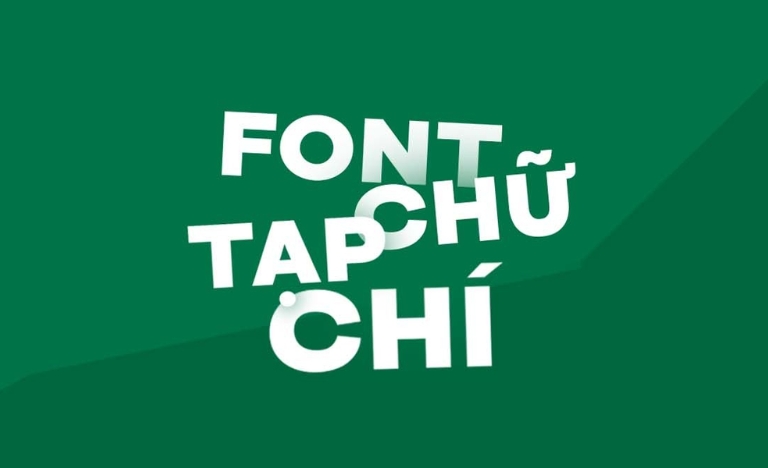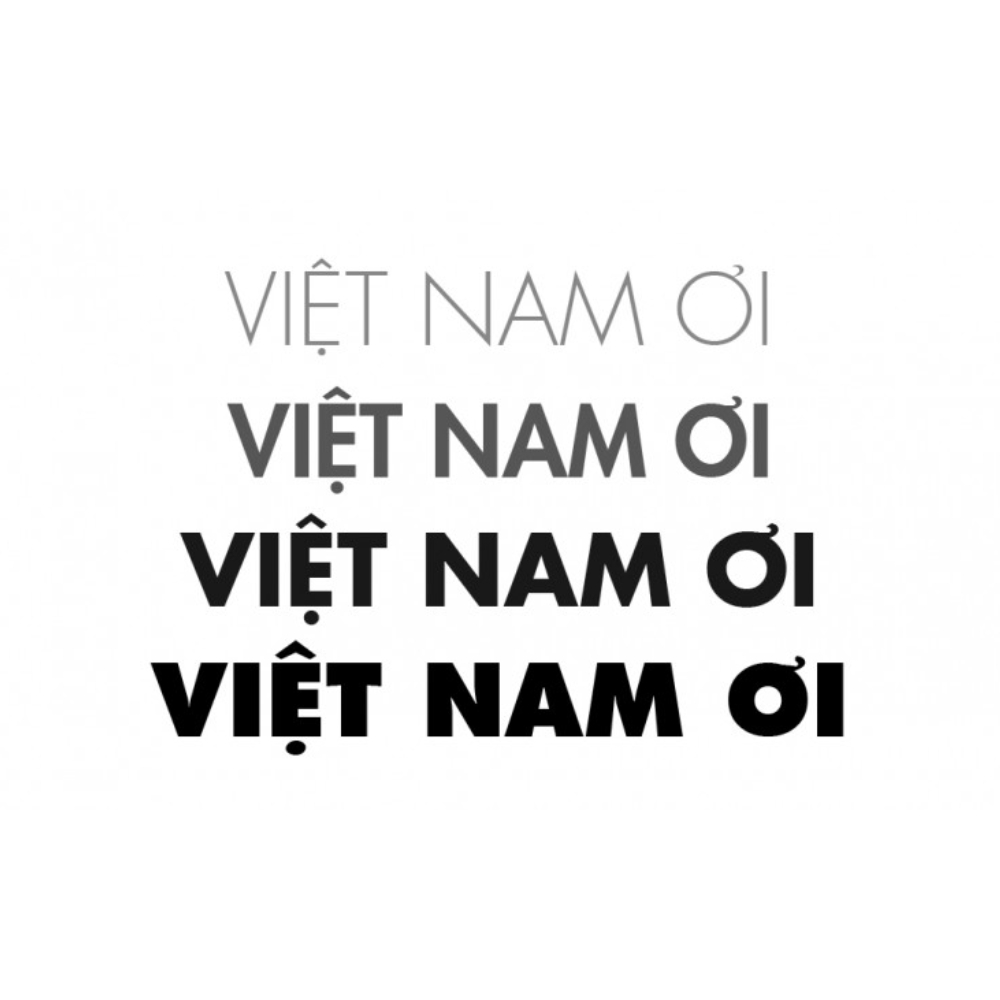
Trong lĩnh vực thiết kế đồ họa và trình bày hồ sơ kiến trúc, việc sử dụng các bộ font chữ tạp chí Việt hóa giúp nâng tầm thẩm mỹ, mang lại vẻ ngoài sang trọng và chuyên nghiệp cho văn bản. Đặc trưng của dòng font này là sự chỉn chu trong cấu trúc và khả năng thu hút thị giác mạnh mẽ, phù hợp cho các bìa hồ sơ dự án, brochure giới thiệu homestay hay các ấn phẩm truyền thông cao cấp.
Đặc điểm thẩm mỹ của các dòng font chữ tạp chí Việt hóa
Dòng font này thường được chia thành hai nhóm chính: nhóm có chân với độ tương phản cao mang nét cổ điển, thanh lịch và nhóm không chân tối giản mang hơi thở hiện đại. Điểm nổi bật của font chữ tạp chí Việt hóa chính là việc tối ưu hóa bộ dấu tiếng Việt sao cho cân đối với các đường nét thanh đậm đặc trưng, giúp văn bản duy trì được sự đẳng cấp của bộ chữ gốc mà không gặp tình trạng lỗi hiển thị ký tự.
Sự ổn định của các bộ font này còn thể hiện ở khả năng định hình phong cách cho toàn bộ bản thiết kế. Những đường nét sắc sảo, dứt khoát giúp các tiêu đề trở nên nổi bật, tạo ra nhịp điệu thị giác lôi cuốn cho người đọc. Đây là lựa chọn phù hợp cho những ai muốn tìm kiếm sự giao thoa giữa tính nghệ thuật của font chữ báo chí truyền thống và sự linh hoạt của xu hướng thiết kế đương đại.
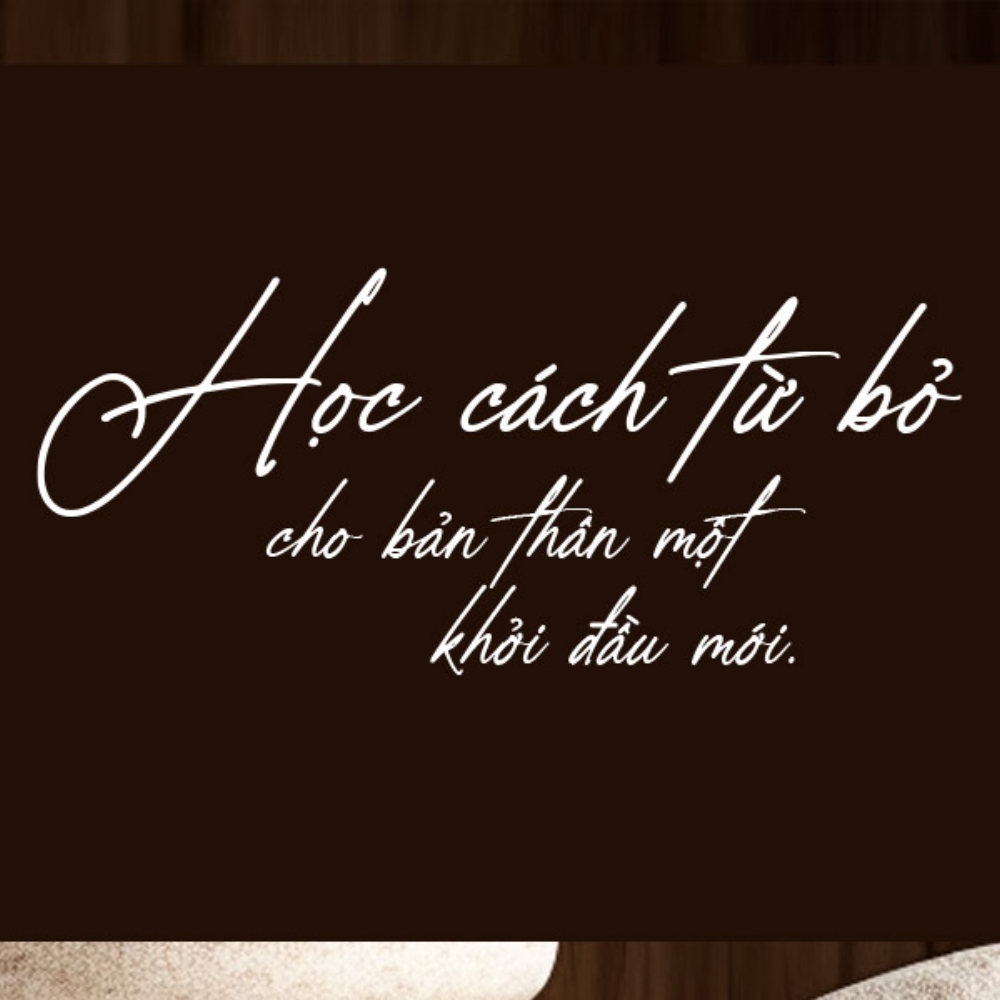
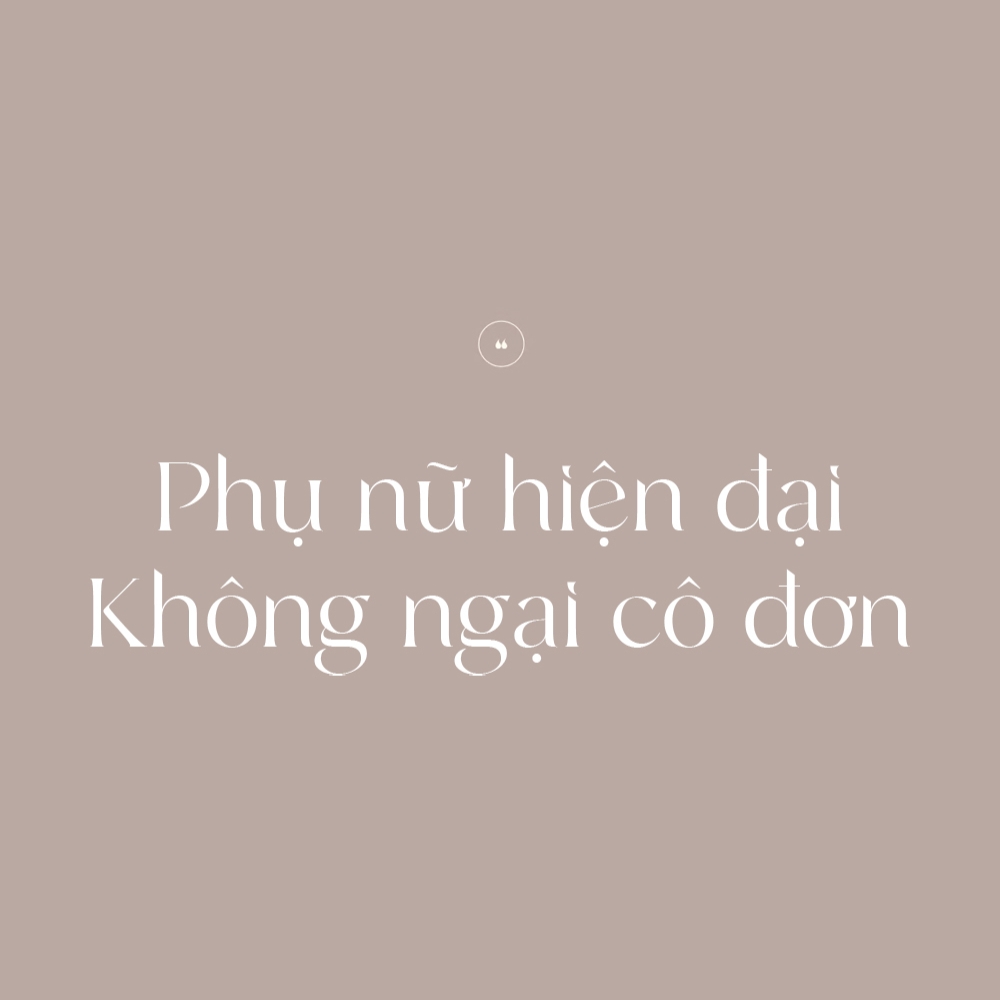
Phân loại và tải các nhóm font chữ báo chí và thời trang phổ biến
Tùy vào mục tiêu truyền tải và đối tượng người xem, bạn có thể lựa chọn các nhóm font chữ phù hợp để đạt được hiệu quả thị giác như mong muốn.
| Nhóm Font | Đặc điểm thiết kế | Mục đích sử dụng |
|---|---|---|
| Didone / Modern Serif | Tương phản nét thanh đậm cực cao, sang trọng | Font chữ tạp chí Vogue, thời trang cao cấp |
| Transitional Serif | Cân đối, dễ đọc, mang tính chính thống | Nội dung báo chí, thuyết minh dự án kiến trúc |
| Geometric Sans-serif | Hình học tối giản, hiện đại, thông thoáng | Tạp chí kiến trúc, nội thất, phong cách Industrial |
| Humanist Sans | Nét chữ mềm mại, mang hơi hướng viết tay | Tạp chí phong cách sống, đời sống xã hội |
Gợi ý phối hợp: Đối với các hồ sơ năng lực dự án nhà lắp ghép hoặc homestay, bạn nên sử dụng một font chữ tạp chí thời trang cho các tiêu đề chính và kết hợp cùng một font chữ không chân tối giản cho phần nội dung chi tiết. Sự phân cấp này giúp bản thiết kế của bạn trông chuyên nghiệp và mạch lạc hơn.
03 Ứng dụng font chữ tạp chí thời trang vào thiết kế kiến trúc
Nhờ vẻ ngoài giàu tính thẩm mỹ và chuyên nghiệp, bộ font này mang lại giá trị thực tế cao khi được ứng dụng vào các hạng mục quảng bá và trang trí không gian:
- Thiết kế hồ sơ năng lực dự án: Sử dụng Font chữ tạp chí Vogue cho các tiêu đề trang mục giúp thể hiện tư duy thẩm mỹ sắc sảo, tạo ấn tượng mạnh mẽ về năng lực của đơn vị thiết kế đối với chủ đầu tư.
- Nhận diện cho Homestay & Boutique Hotel: Những nét chữ thanh lịch của dòng font thời trang rất ăn ý khi xuất hiện trên các bảng hiệu mica, inox gương hoặc các ấn phẩm hướng dẫn khách hàng tại khu nghỉ dưỡng.
- Bảng biển trang trí nội thất: Bạn có thể dùng font này để làm decal dán tường hoặc in tranh trang trí tại sảnh chờ văn phòng container, mang lại cảm giác thời thượng và đẳng cấp cho không gian sống và làm việc.
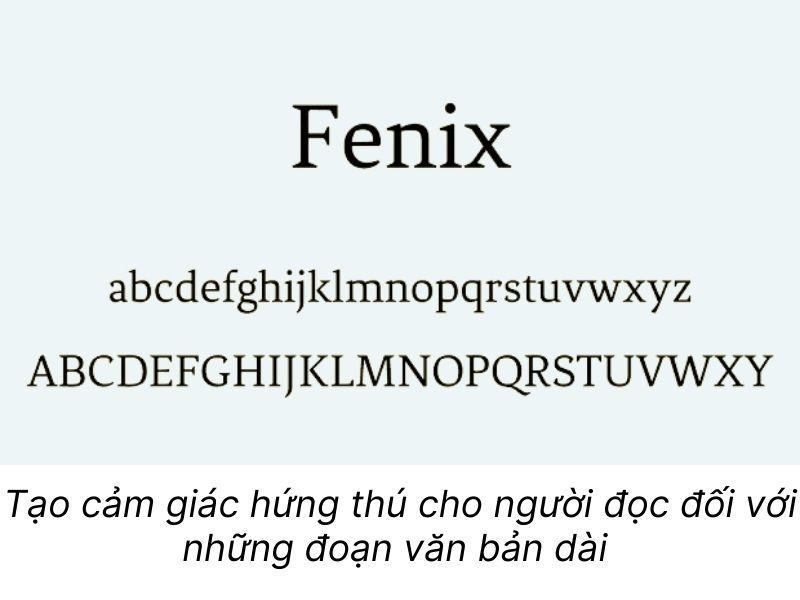
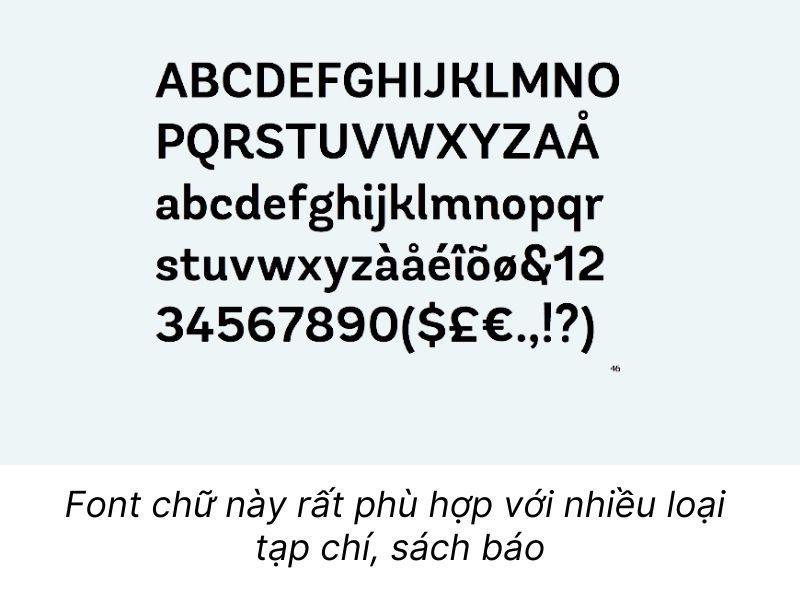
03 Lưu ý để trình bày bản thiết kế mang phong cách tạp chí chuyên nghiệp
Để khai thác hiệu quả vẻ đẹp của các bộ font này mà không làm rối mắt người xem, người thiết kế nên lưu tâm một số kinh nghiệm sau:
- Kiểm soát độ phân giải in ấn: Các font chữ phong cách tạp chí thường có nét thanh cực kỳ mỏng. Khi thực hiện in ấn brochure hoặc poster, bạn cần đảm bảo tệp thiết kế đạt độ phân giải cao để các nét mảnh không bị mất đi hoặc nhòe mờ.
- Nới rộng khoảng cách dòng: Để các dấu tiếng Việt và chân chữ không bị chồng lấn, bạn nên thiết lập khoảng cách dòng thoáng một chút, giúp văn bản trở nên minh bạch và tinh tế hơn.
- Hạn chế dùng quá nhiều kiểu chữ: Chỉ nên sử dụng tối đa 2 đến 3 loại font chữ khác nhau trong một bản thiết kế để duy trì tính đồng bộ và chuyên nghiệp cho tổng thể ấn phẩm.